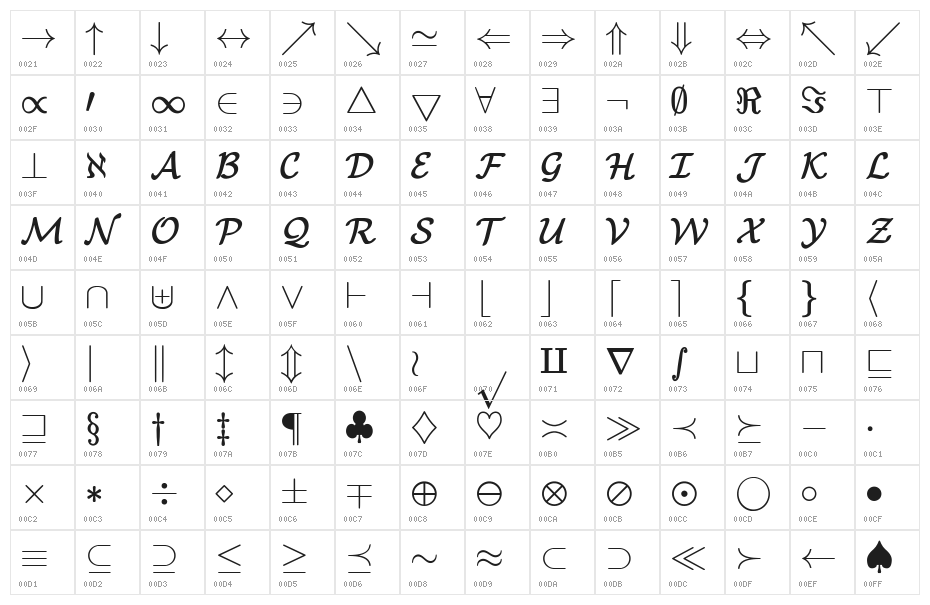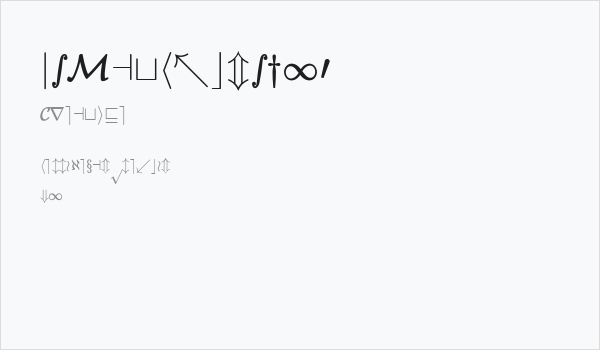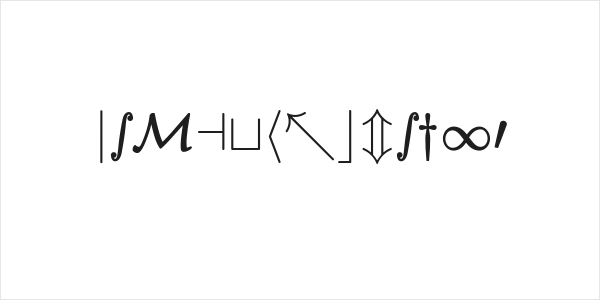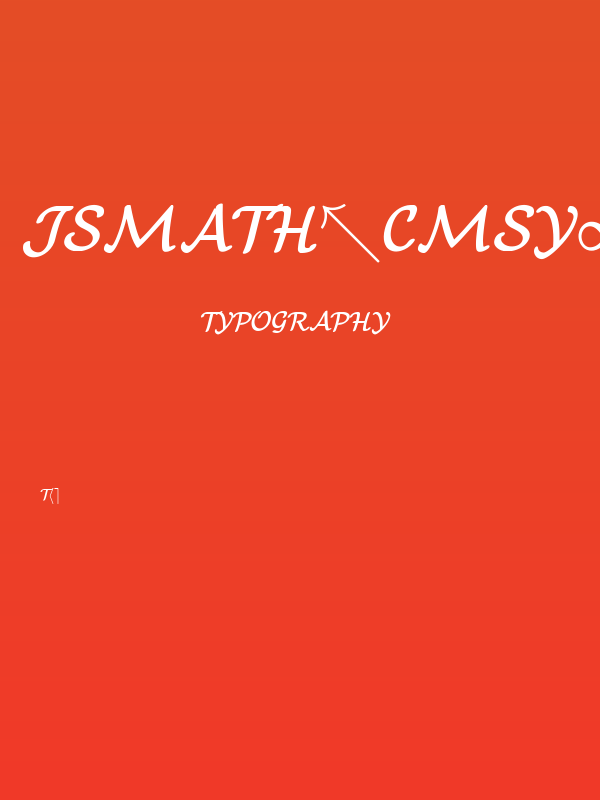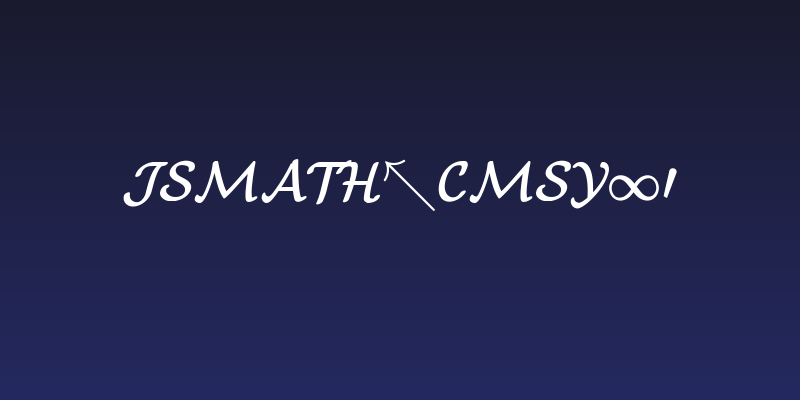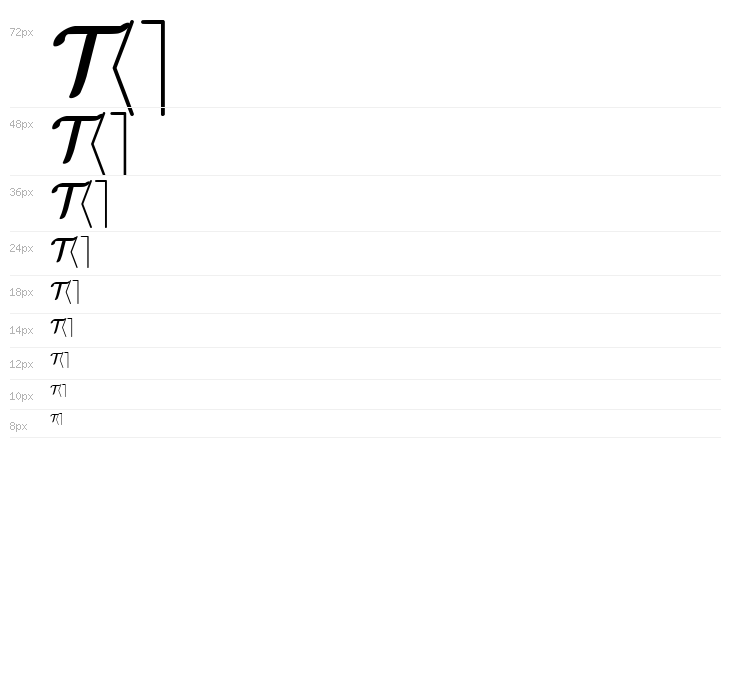
jsMath-cmsy10 Font
| Caz de utilizare | Technical documents, educational materials, academic papers. |
| Proiecte propuse | Ideal for academic papers, technical documents, and educational materials requiring mathematical notation. |